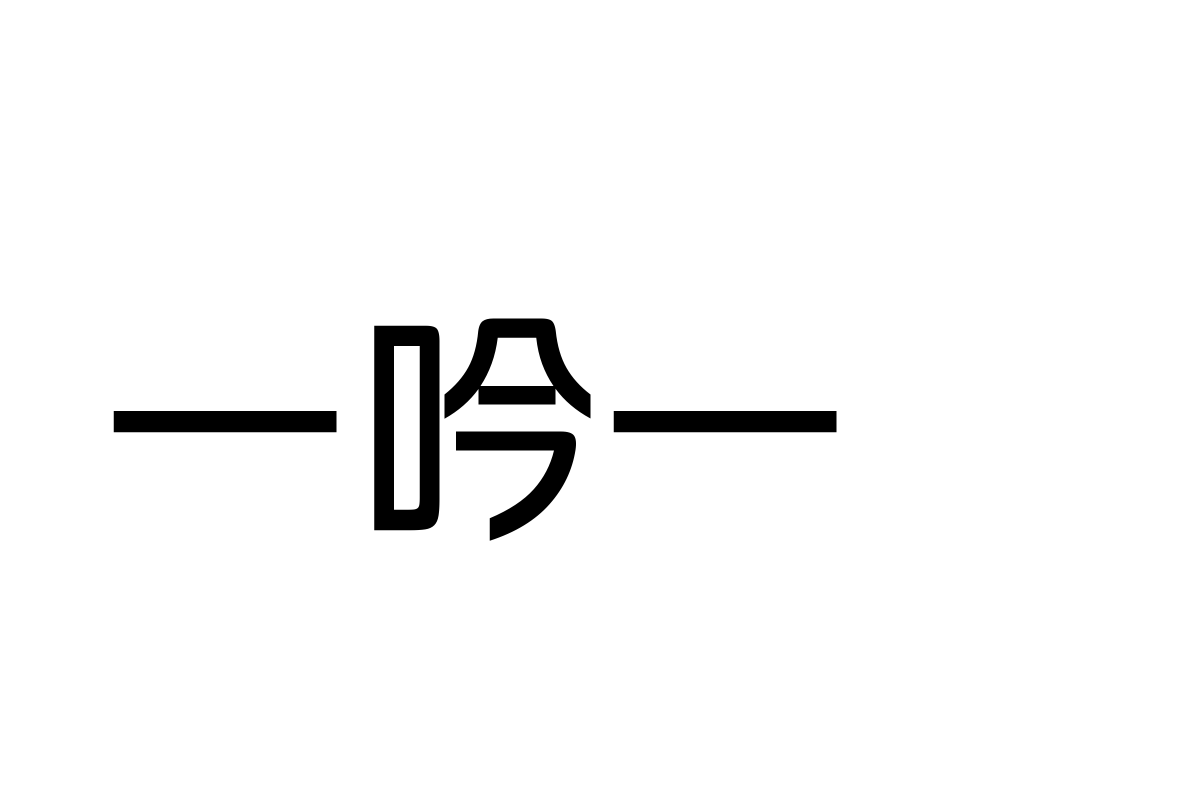
汉仪风尚黑b5-55是一款现代而优雅的中文字体,具有独特的设计和风格。这款字体由汉仪公司设计,以其简洁、清晰的字形和流畅的笔画线条而受到广泛好评。
字体特点:
1. 字形结构紧凑,线条流畅,给人一种简约而时尚的感觉。
2. 笔画粗细适中,既有力度又有柔美,适合用于标题、正文等多种场合。
3. 字间距均匀,排版整洁,有利于阅读和打印。
4. 适用于各种印刷品,如书籍、杂志、报纸、广告等。
应用场景:
1. 书籍封面、内页排版
2. 杂志、报纸的标题与正文
3. 广告设计中的标题与正文
4. 企业宣传册、产品说明书等
5. 网站、博客等网络媒体的文字设计
总之,汉仪风尚黑b5-55是一款非常实用的中文字体,无论是在印刷还是电子媒体中都能展现出其独特的魅力。